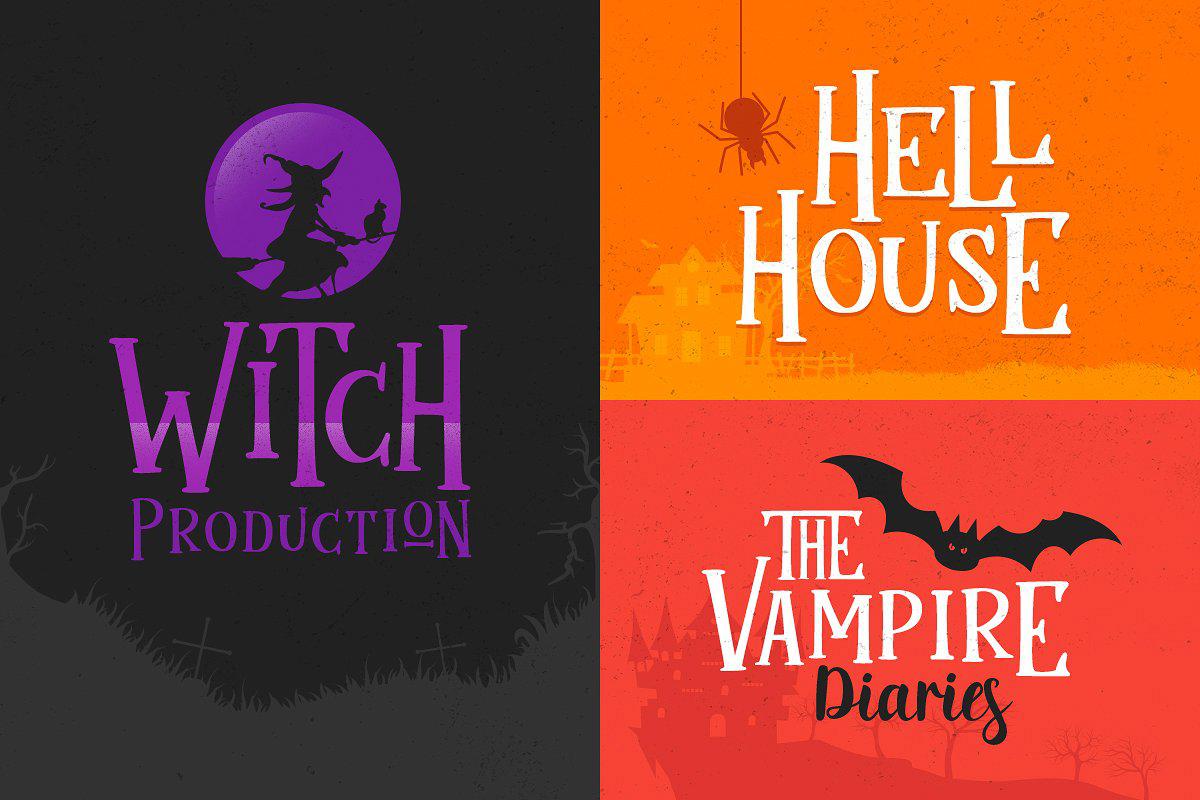
此字体由两种字体组成,一种是字体,另一种是serifandscript.mukaduameans,这两种字体可以在高兴和不高兴的情况下使用,但仍然看起来像是创作主题/恐怖/恐怖概念!MainFontIsa系列具有唯一弹跳基线的字体,包括大写和小写字符、标点符号、数字和多语言支持。它还具有五种类型功能,包括类型列表替换项和规则!此字体由两种字体组成,一种是字体,另一种是serifandscript.mukaduameans,这两种字体可以在高兴和不高兴的情况下使用,但仍然看起来像是创作主题/恐怖/恐怖概念!MainFontIsa系列具有唯一弹跳基线的字体,包括大写和小写字符、标点符号、数字和多语言支持。它还具有五种类型功能,包括类型列表替换项和规则!